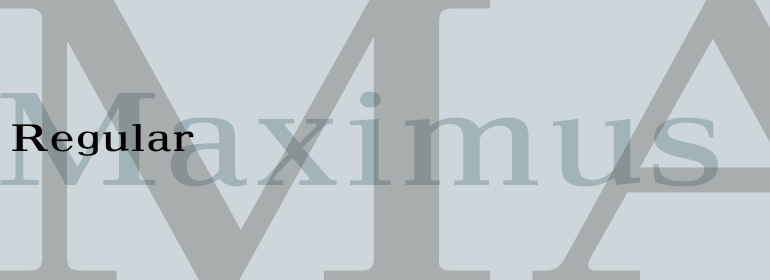
Maximus®
Walter Tracy于1967年设计了Maximus字体,同年与Linotype Ltd一起出现在英格兰。Maximus原本是一款报纸字体,它有两个字重,可用于小型广告。
此处所提供的较粗的字重是专门为强调文本列而开发的。
总体上来说,该字母表的设计比大多数字体的字母更宽,以加强小尺寸字体的可读性。
这样可以确保引起读者的注意,特别是当它与其他字体混合使用时。Maximus字体的大写字母特别适合用作首字母。
Walter Tracy designed Maximus font in 1967, when it appeared with Linotype Ltd in England. Maximus was originally intended as a newspaper typeface with two weights for small ads.
The bolder weight offered here was developed especially for emphasis within columns of text.
The alphabet as a whole has a broader design than most types to increase legibility in smaller point sizes.
This ensures that it will draw the reader's attention, especially when it is mixed with other typefaces. The capitals of Maximus font are a good choice for use as initials.